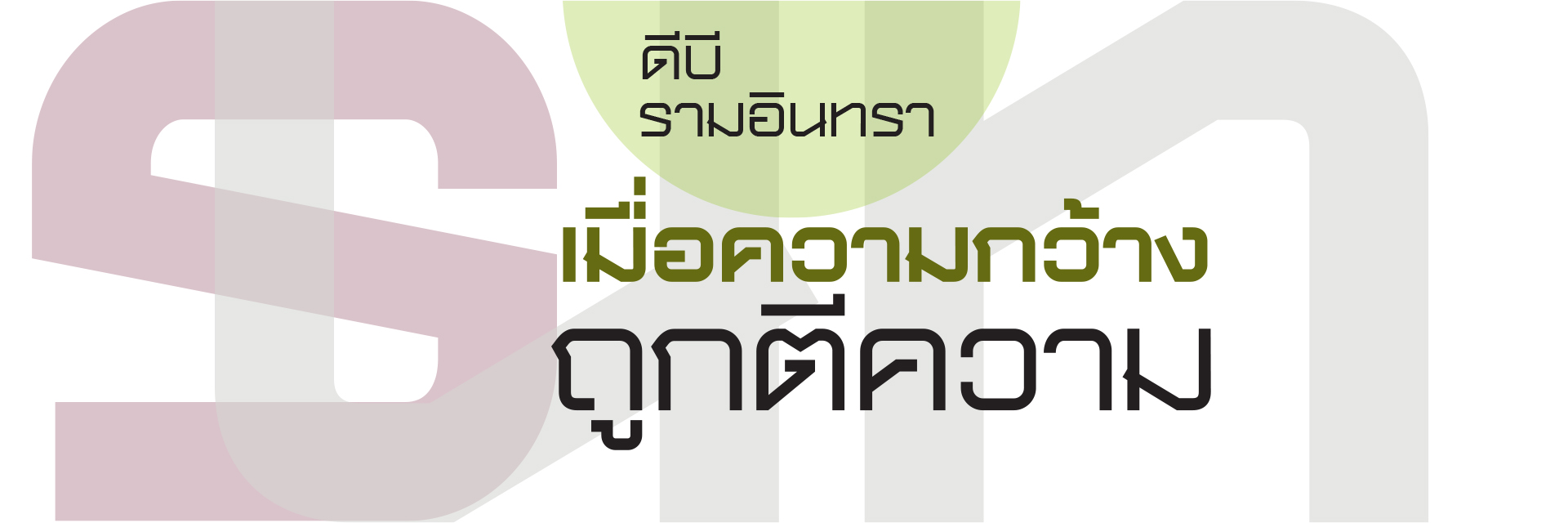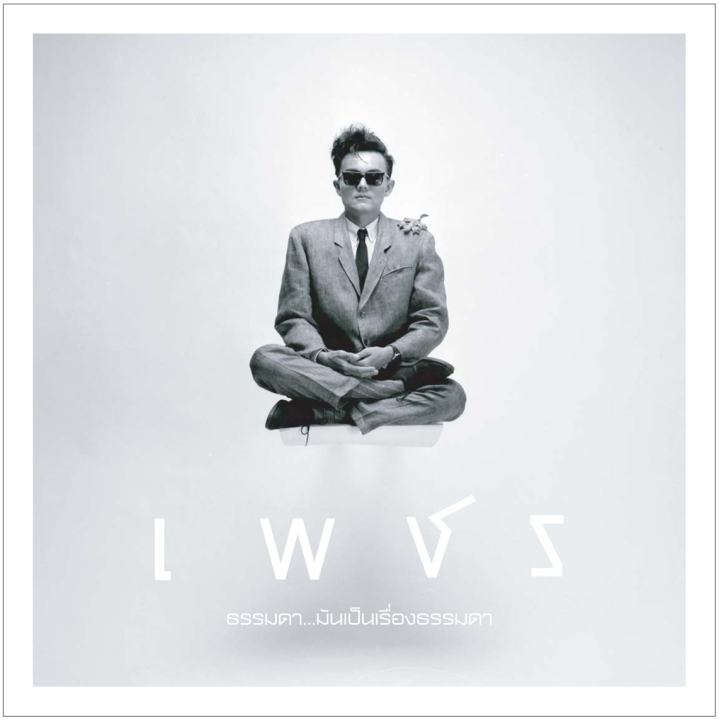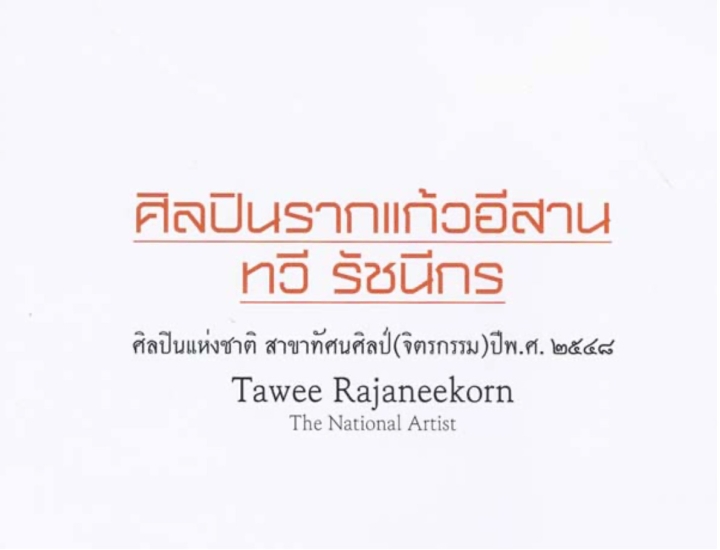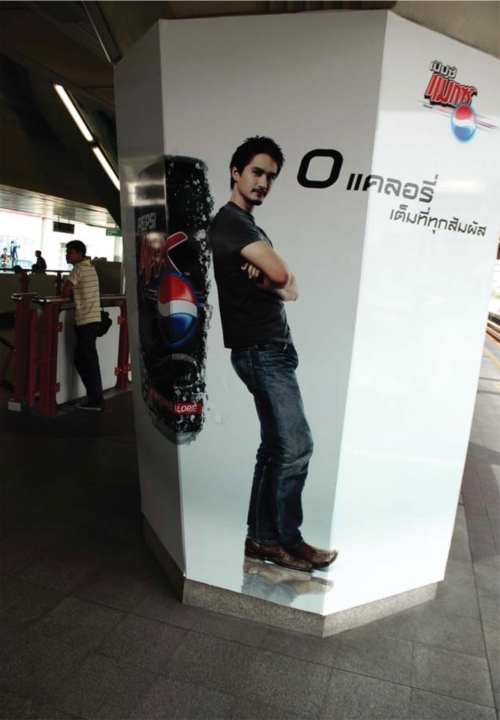
ความกว้างของรูปอักษร (glyph) ให้ความรู้สึกโอ่อ่า ฐานที่กว้างให้ความรู้สึกมั่นคง. รูปทรงจัตุรัสที่เกิดจากเส้นน้ำหนักเดียว (Monoline) ให้ความรู้สึกทันสมัยเรียบง่าย. เมื่อถูกลบมุมช่วยลดความแข็งลง. ถ้าเส้นบางจะเหมือนห้องปลอดโปร่ง ถ้าเส้นหนาจะดูหนักแน่นแข็งแรง. นี่คือความเป็น Eurostile Extended.
Eurostile ซึ่งเน้นกรอบเหลี่ยมมากกว่าโค้งนั้น เหมาะสมเป็นตัวพาดหัว (ทั้ง Display และ Subhead) มากกว่า. ถ้ามันถูกใช้เป็นตัวเนื้อ (text) ให้อ่านยาวๆ จะ สู้ Helvetica ไม่ได้ เพราะอ่านยากกว่าพอสมควร. อย่างไรก็ตามแบบตัวพิมพ์ Eurostile ได้ส่งอิทธิพลต่อแบบตัวอักษร ไทยที่มีหัวและไม่มีหัว.
แบบตัวอักษรลอกที่ได้รับอิทธิพลมาจาก Eurostile ได้แก่ มานพ 14 ที่ละหัวไว้เป็นเส้นขีดสั้นๆ ในแนวนอน. ลักษณะที่มีหัวกลม หรือมีหัวแอบแฝงสั้นๆ ถูกมองว่าอนุรักษ์นิยมจนเกินไปในยุคนี้ (ซึ่งเป็นเรื่องน่าเสียดาย) และถูกแทนค่าด้วยตัวอักษรไทยเส้นเดี่ยว (Monoline) ที่ละหัวมากขึ้น (เช่น ตัว น, บ, ม, พ ไม่มีหัวก็อ่านออกอยู่แล้ว แต่ ผ, ภ, ถ ยังไงก็ ต้องมีขีดหัวให้เห็น)
ธรรมดา : ปก CD งาน remaster ชุด “เพชร : ธรรมดา มันเป็นเรื่องธรรมดา” คําว่า “เพชร” ไม่ใช่ตัวพิมพ์ธรรมดา ถูกประดิษฐ์ขึ้นเมื่อ 20 ปีที่แล้ว ส่วนคํา “ธรรมดา มันเป็นเรื่องธรรมดา” ใช้ DB Ramintra น้ําหนักธรรมดา (Regular) ซึ่งสะท้อน “เหลี่ยมคม ของความเป็น “เพชร” ด้วยเส้นทะแยง ที่เป็นลักษณะเด่นของฟอนต์
รากไทย : หนังสือ "ศิลปินรากแก้วอีสาน : ทวี รัชนีกร" (crop จากหน้า ๑) ผู้ออกแบบต้องการเน้นบุคลิกของอาจารย์ทวี ที่เป็นนักสัจจะนิยม. การใช้ตัวพิมพ์ที่มีรากของความเป็นไทยอย่าง DB Ramintra ถือเป็นการให้เกียรติศิลปินแห่งชาติ.
ดังนั้น ผมจึงลองตั้งโจทย์ดูว่า ถ้าเราจะออกแบบฟอนต์ไทยที่ดูเหลี่ยมๆ กว้างๆ เหมือน Eurostile Extended โดยมีโจทย์ว่าเป็นตัวที่ตัดทอนหัวที่ไม่จําเป็นออก แต่ยังให้สําเนียง ไทยแท้อยู่ ผมควรจะทําอย่างไร?
ระหว่างร่างตัวอักษรตามโจทย์ที่ว่านี้ ตัวอักษรที่เขียนประดิษฐ์ด้วยพู่กันปากแบนในโปสเตอร์หนังยุคเก่าๆ ที่เคยเห็นตั้งแต่เด็กได้ผุดขึ้นมาในสมอง จําได้ว่ามันอ่านง่ายเป็นบ้าเลย! เพื่อให้หายสงสัยว่าทําไมมันอ่านง่าย ผมลองเขียน ก ถึง ฮ ดูในกระดาษแล้วพบความจริงว่า มีตัวเขียนมาตรฐานของไทย จํานวนเกินครึ่งหนึ่งที่ประกอบขึ้นด้วยเส้นแนวทะแยง ชันบ้าง (เช่น ง, ท, พ, ห) ลาดบ้าง (เช่น น, ผ, ม), เมื่อเปรียบเทียบดูพบว่า ตัวเขียนโปสเตอร์ด้วยพู่กันปากแบนของช่างเขียนยุคเก่าได้ถ่ายทอดเส้นแนวทะแยงซึ่งเป็น DNA ของตัวอักษรไทยมาตรฐานไว้ได้อย่างชัดเจน เกิดเป็นตัว “Thai Display” ที่ใสซื่อสุดๆ (แม้ทุกวันนี้ไม่มีคอมฯ ไม่มีเงินค่าพิมพ์ inkjet ขอแค่มีผ้า, สี, แปรง, และฝีมือ ก็สามารถพึ่งพาตัวเองได้!) มันทําให้ผมสรุปได้เป็นคําตอบว่า ถ้าไม่มีหัวชัดๆ ให้เน้นเส้นทะแยงชัดๆ เดี๋ยวก็ดูเป็นไทยเอง ผลที่ได้ออกมาคือฟอนต์ที่ดูต่างไปจาก Eurostile Extended คือเรียบง่ายน้อยลง แต่ดูคม และชัดถ้อยชัดคํา เปรียบเป็นถนนก็ชื่อประมาณ รามอินทรา ที่กว้างขวาง, ชื่อฟังดูเป็นไทยๆ แถมเสียงคําท้าย “ทรา” ฟังดูเข้มแข็งหนักแน่น ไม่หน่อมแน้ม. จึงให้ชื่อว่า DB Ramintra. ลักษณะเส้นแนวทะแยงชัดๆ แบบนี้ ผมยังได้นําไปใช้กับฟอนต์อีกตัวหนึ่ง คือ DB PenThai ซึ่งดูเป็นไทยสมชื่อมาก เป็นการนําตัว Thai Display ยุคโปสเตอร์ผ้าที่ใสซื่อมาปรับปรุง โดยการ เปลี่ยนเส้นบนจากเส้นตรงเป็นเส้นโค้งแทนให้ดูร่วมสมัยขึ้น
ไทยทะแยง : บน DB Ramintra เทียบกับล่าง DB PenThai. เป็นการนำเส้นทะแยงจากตัวอักษรที่เขียนด้วยพู่กันในอดีต มาออกแบบใหม่ด้วยรูปทรงที่แตกต่างกัน.
ตัวอย่างการเลือกฟอนต์เหลี่ยมๆ กว้างๆ ที่เข้ากันได้ดีกับ Headline คือ “คํานําเทรนด์” ของโค้ก และ “0 แคลอรี่ เต็ม ที่ทุกสัมผัส” ของเป๊ปซี่ ซึ่งออกมาชนกัน, ในขณะที่โฆษณา แบรนด์ซุปไก่ทาง TV ชุดที่มี “หนู” แปรงคู่สะบัดเส้นซึ่งดูดี มากนั้น ใช้ฟอนต์ที่ดูทันสมัยกว่า ทว่าอ่านยากเกินไปสําหรับ สื่อ TV ที่มีเวลาให้อ่านจํากัดเป็นวินาที
นำเทรนด์ : Light Box ของโค้ก เลือกใช้ฟอนต์ PSL NatrinthornExtra ที่กำลัง intrend ได้เข้ากับพาดหัวเป็นอย่างดี แม้ว่า Eurostile ซึ่งเป็นฟอนต์ต้นแบบจะเกิดตั้งแต่ปี ค.ศ. 1962 (โดย Aldo Novarese) แล้วก็ตาม.
แจกให้ชัด : "บาวแดงแจกมอเตอร์ไซด์" ตัวอักษร จ ของฟอนต์ PSL NatrinthornExtra ถูกศัลยกรรมโยกคอให้เอนเห็นเด่นชัด ช่วยให้อ่านง่ายขึ้น. เป็นตัวอย่างความพยายามแก้ปัญหาด้วยตัวเองของนักออกแบบที่น่าชื่นชม.
เต็มที่ทุกสัมผัส : ด้วยเลย์เอ้าท์ที่ intrend อยู่แล้ว เป๊ปซี่เลือกใช้ DB Ramintra ก็โดนเลย เส้นทะแยงของรูปอักษรให้สัมผัสที่ซาบซ่า, ตัว Bold Italic ให้ความรู้สึกเต็มที่อย่างมีพลวัตร.
การเลือกฟอนต์ที่ดูแล้วได้บุคลิกขององค์กร, สินค้า หรือได้บุคลิกของกลุ่มเป้าหมายที่ต้องการสื่อถึง ฯลฯ อาจฟังดูง่าย. ปัญหาไม่คาดคิดที่ตามมากลับพบได้บ่อยๆ ว่าอ่านได้ยาก (ทั้งๆ ที่ตั้งใจใส่ลงไปให้อ่านไม่ใช่แค่ดู). ความผิดพลาดเช่น นี้จะไปโทษฟอนต์ไม่ได้, โทษคนออกแบบฟอนต์ก็ไม่ได้อยู่ดี. เป็นความรับผิดชอบของนักออกแบบรวมไปจนถึงผู้อนุมัติแบบก่อนถูกผลิตเป็นชิ้นงานสื่อที่จะต้องหาความรู้ เพื่อสังเกตให้เป็นว่าฟอนต์ตัวไหนเหมาะที่จะใช้ในขนาดไหน (ขนาดสัมพันธ์โดยตรงกับระยะห่างที่ใช้อ่าน) และเหมาะที่จะใช้กับสื่อประเภทไหน (ฟอนต์ที่มีตัวที่สับสนกันมากๆ ต้องให้เวลา อ่านอย่างพอเพียง).
ไม่มีฟอนต์ใดในโลกเป็นยาครอบจักรวาลแก้ปัญหาได้ทุกโจทย์งานสร้างสรรค์ การที่จะประสบความสําเร็จนั้นต้องซ้อม (ตีความให้ถูก), ซ้อม (เลือกให้เป็น), ซ้อม (พิมพ์มาวางเลย์เอาท์ดู) และก็ซ้อม (อ่านให้มั่นใจก่อนใช้จริง) เท่านั้น.